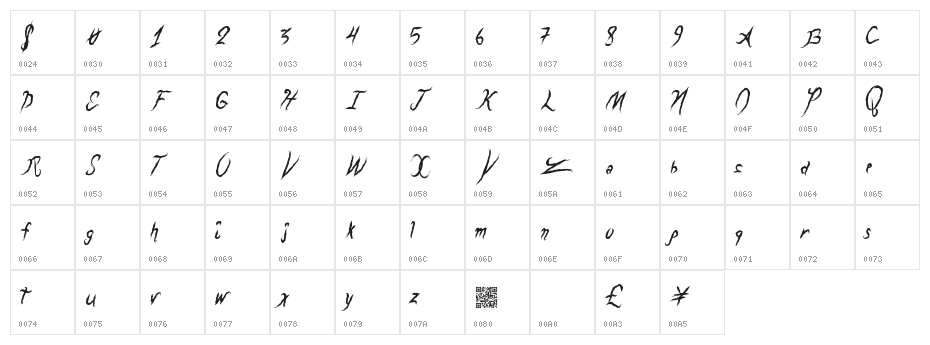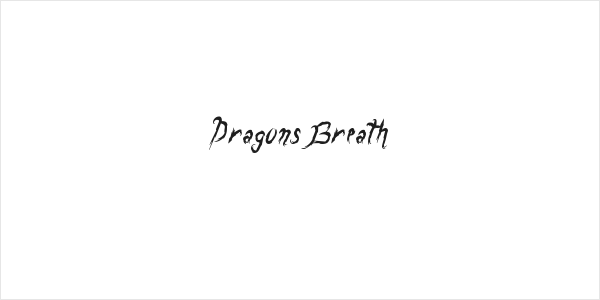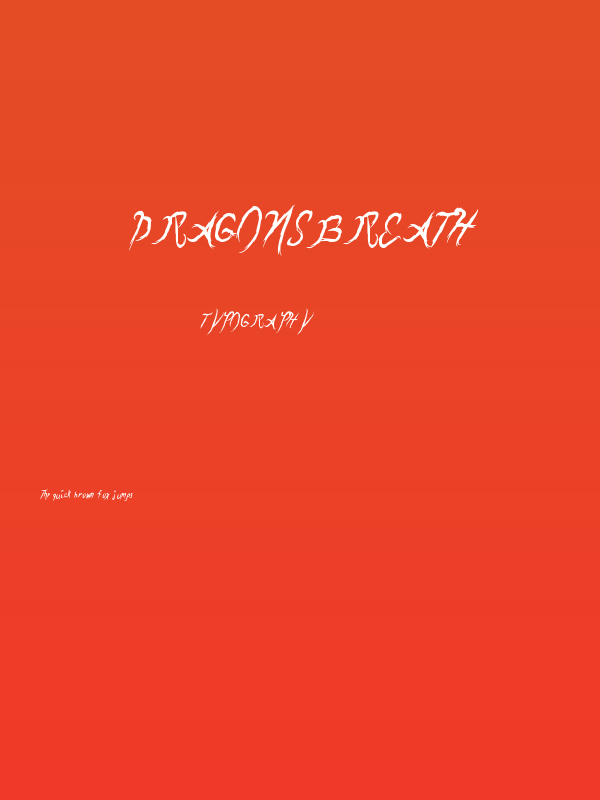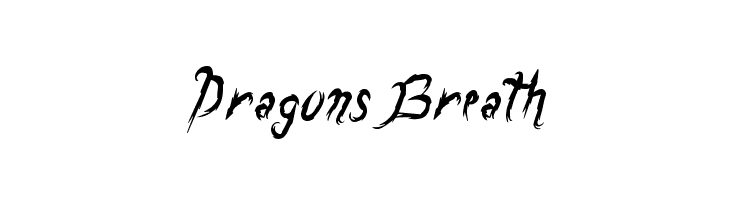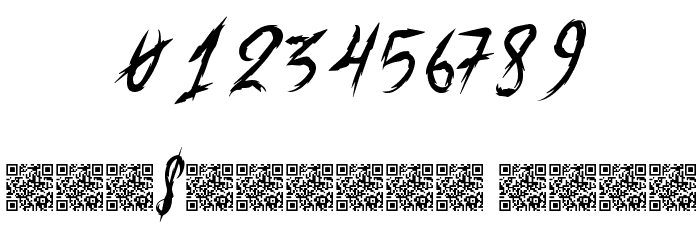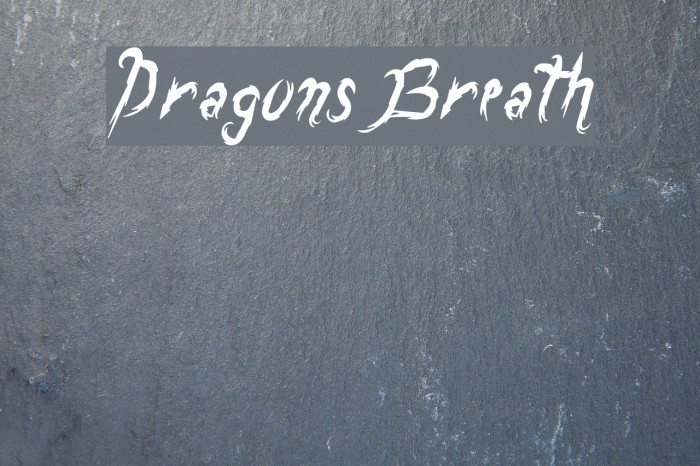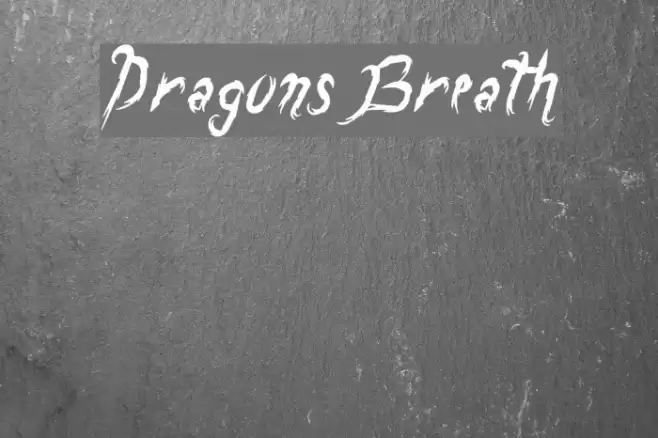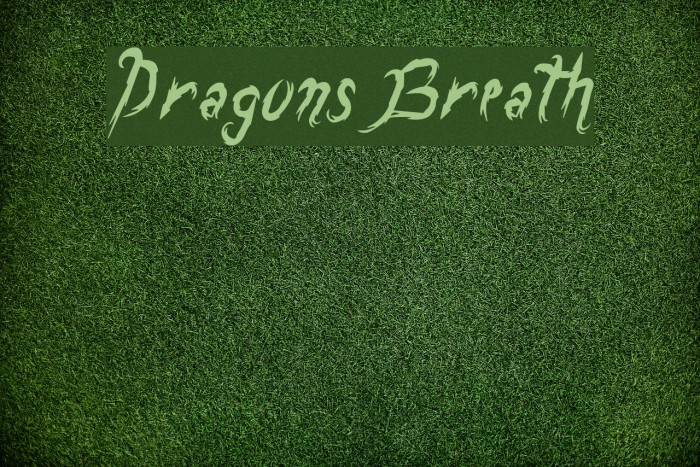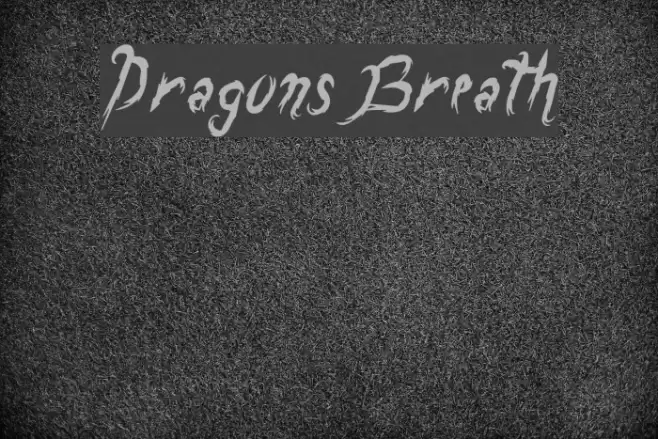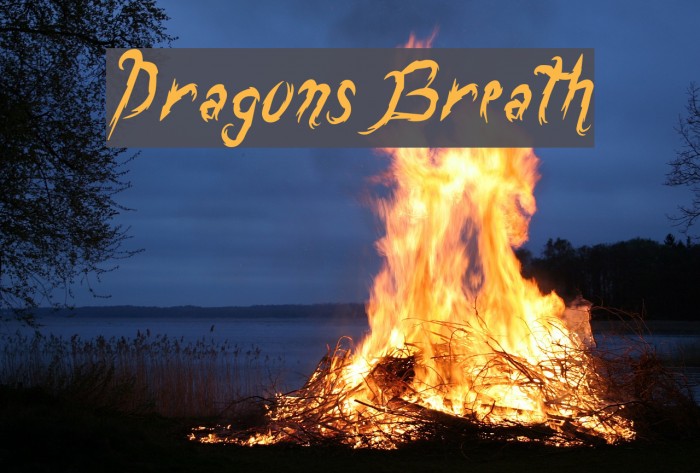
DragonsBreath Font
| Vorgeschlagene Projekte | Ideal for fantasy-themed designs, video game titles, movie posters, or any project requiring a bold and dramatic typeface. |